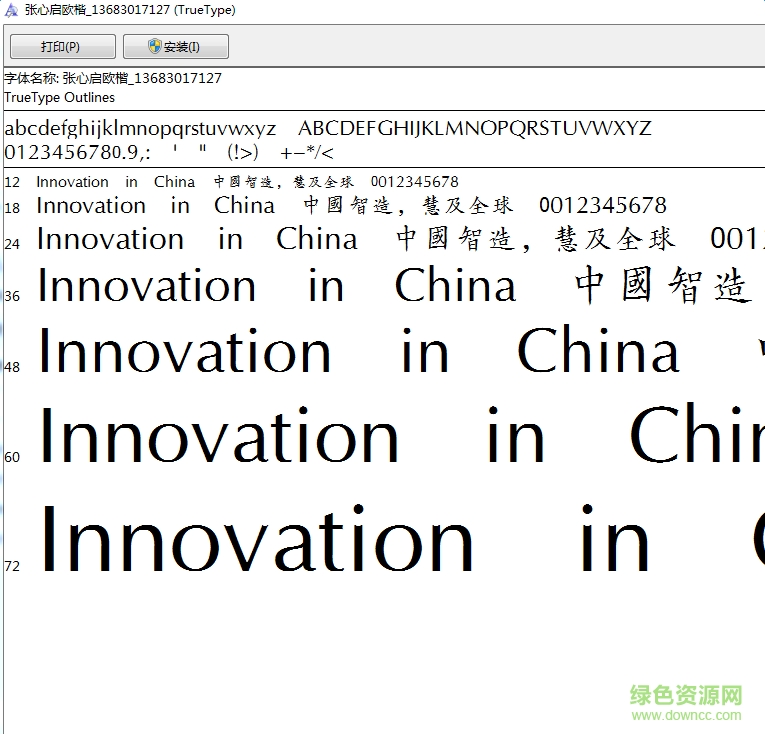
張心啟歐體楷書繁體是一款以張心啟書法家為背景的歐楷風(fēng)格字體,歐體楷書筆畫隨意灑脫,棱角突出,創(chuàng)意獨特,別有一番韻味,深受廣大書法家喜愛,還有更多好看字體下載,歡迎來綠色資源網(wǎng)體驗!
楷書也叫正楷、真書、正書。由隸書逐漸演變而來,更趨簡化,橫平豎直。《辭?!方忉屨f它“形體方正,筆畫平直,可作楷?!?。這種漢字字體端正,就是現(xiàn)在通行的漢字手寫正體字。
此字體筆畫十分工整,配上繁體的古典優(yōu)雅,用于書法藝術(shù)設(shè)計再合適不過了,非常的賞心悅目,感興趣的朋友歡迎到綠色資源網(wǎng)下載!